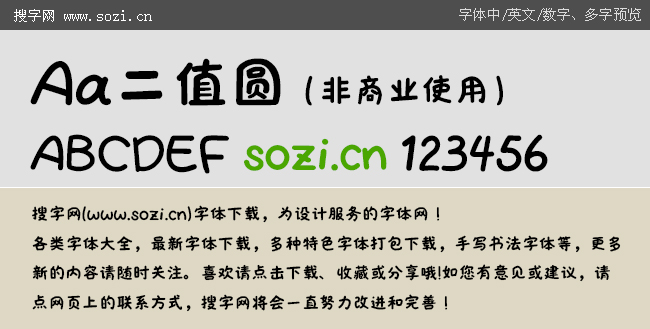
Aa二值圓
搜字網(wǎng)給大家提供一款Aa二值圓(非商業(yè)使用)中文字體下載,Aa二值圓是一款卡通風格的手寫字體,這款字體字形圓潤可愛,富有趣味性,具有很好的視覺感。適合應用于藝術(shù)設計、平面宣傳設計、網(wǎng)頁設計、海報設計等應用(此字體為個人非商用版,商用可以聯(lián)系QQ:1006760504)。